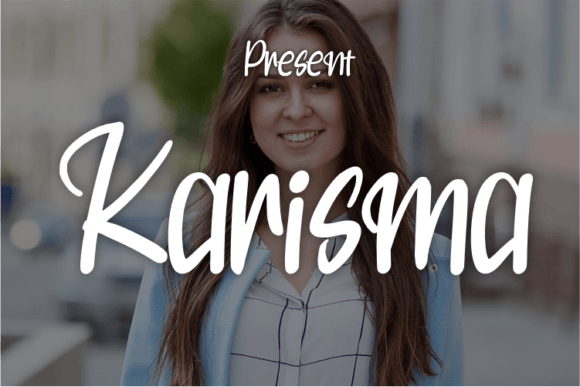
Karisma
Karismaのような高品質の素材をお探しの場合、このプレミアムパッケージはクリエイティブなプロジェクトに素晴らしい選択です。
精密に作られたKarismaは、クリーンなベクター、滑らかなタイポグラフィ、そして安心のための商用ライセンスを提供します。
POD(オンデマンド印刷)製品、結婚式の招待状、またはソーシャルメディアのグラフィックを作成している場合でも、Karismaは理想的です。